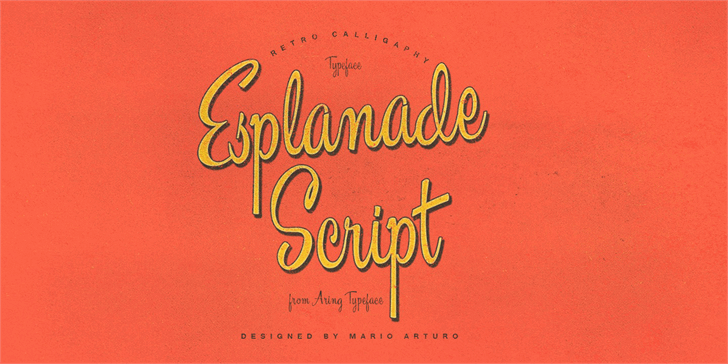
Esplanade Script font
A Esplanade Script é uma fonte de script perfeita para projetos que exigem um estilo elegante e sofisticado. Inspirada no traçado artesanal, essa fonte combina facilmente elementos romanos clássicos com detalhes delicados, criando um resultado único que pode ser usado em diversos ambientes gráficos. Construída pelo talentoso designer Hamilton, a Esplanade Script oferece uma variedade de opções para personalização. Suas curvas fluidas e traços leves permitem criar textos com um encanto especial, tornando-a uma escolha ideal para projetos como cartazes, logotipos e design editorial. Com uma aparência delicada que pode ser muito usada em designs modernos ou clássicos, a Esplanade Script não só traz beleza à sua obra, mas também um toque personalizado. Visite o site do designer para adquirir um licenciamento comercial desta fonte única. Seja você um designer gráfico profissional procurando por uma font que destaque seu trabalho ou um iniciante buscando algo refinado e elegante, a Esplanade Script é certamente a escolha perfeita.